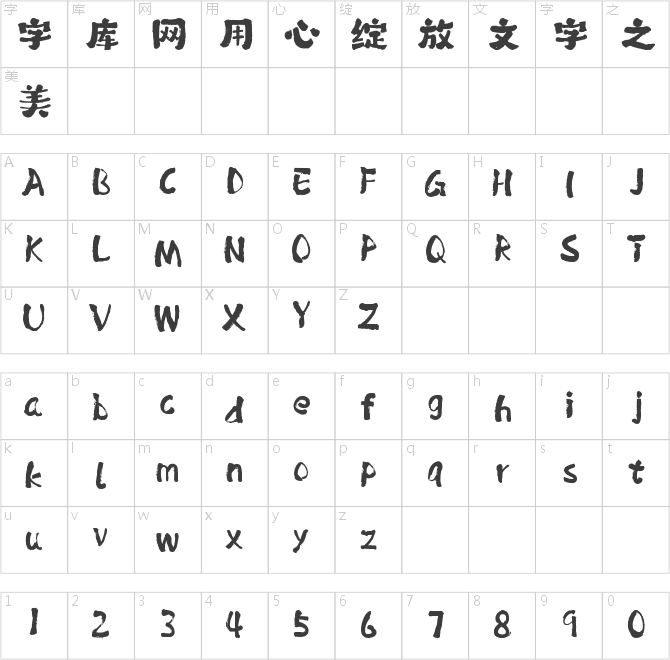
字体名称: 山海白茶手书W
山海白茶手书W
山海白茶手书W介绍
山海白茶手书,是一款卡通风、毛笔字体,包含简繁汉字9169个。这款字体的在传统毛笔字体上融入卡通书写感,书写手法轻盈流动,用笔轻松随性,整体给人一种放松柔美的视觉效果。笔画的飞白效果使字体的气息更加流畅,笔画间的关系密不可分,同时也增加了字体的自由洒脱之感。